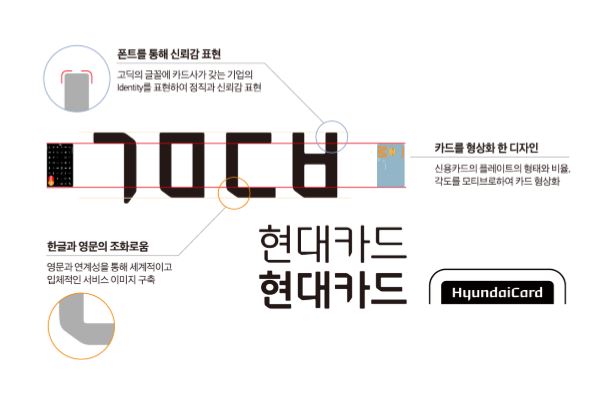
브랜드가 타이포브랜딩을 꼭 해야 하는 이유 5가지
깔끔하면서도 부드러운 느낌의 샌프란시스코(San Francisco)는 애플 폰트로 불릴 만큼 애플의 상징이 되었다. 사용자들은 샌프란시스코체만 보고도 애플을 떠올린다. 이처럼 타이포를 활용한 기업의 브랜딩 활동을 타이포브랜딩이라고 한다. 타이포브랜딩은 어떻게 브랜드의 성공비결이 되었을까? 다섯 가지의 이유를 꼽아봤다.
1. 브랜드의 고유한 목소리가 된다.
기업의 전용서체는 목소리로 비유할 수 있다. 좋은 목소리를 지닌 가수의 음색이 기억에 남듯이, 브랜드의 이미지와 어울리는 서체는 소비자의 기억에 오래 남는다.
카카오는 점점 다양한 형태의 플랫폼으로 사업 영역을 확장하면서 통합적인 디자인을 고민했고, 그 시작으로 ‘카카오체’를 산돌커뮤니케이션과 함께 개발했다.
카카오체는 밝고 재미있고, 친근한 느낌의 감성이 잘 녹아낼 수 있도록 기획되었다. 영문 폰트는 세계적인 디자인 회사인 영국의 달튼막(Daltonmaag)에서 담당하였고, 산돌은 서체를 디자인할 때, 영문과 잘 어울릴 수 있도록 하는 데 공을 들였다고 한다. 귀여운 카카오체는 다양한 플랫폼에 쓰이면서도 카카오의 고유한 색깔을 잘 드러내고 있다.
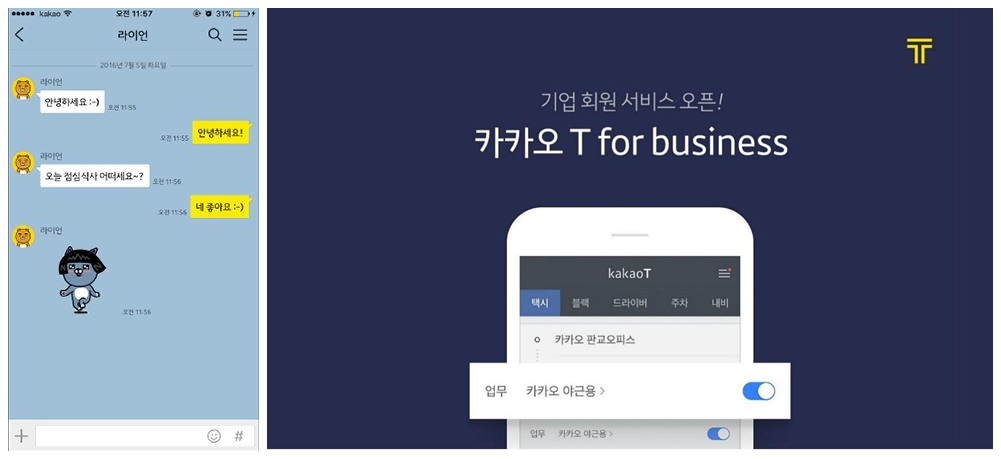
2. 광고비용을 절감할 수 있다.
‘현대카드 유앤아이’ 기업 전용서체는 타이포브랜딩의 대표적인 성공사례로 꼽힌다. 2003년에 제작된 전용서체는 네덜란드 디자인회사 토털 아이덴티티(Total Identity)가 영문 폰트를, 산돌커뮤니케이션이 한글을 개발했다.
카드 모양을 본 따 모서리를 둥글게 디자인함으로써 모던한 느낌을 주며 고딕이 가지는 정직과 신뢰감을 표현했다. 현대카드는 통일된 서체로 브랜딩 활동을 함으로써, 소비자가 서체만 보고도 브랜드를 인식할 수 있게 되었다. 따라서 유명인을 섭외하는데 막대한을 지출을 하지 않고도 타이포만 활용해서 광고제작이 가능했으며, 비용도 절감하는 효과를 가져왔다.
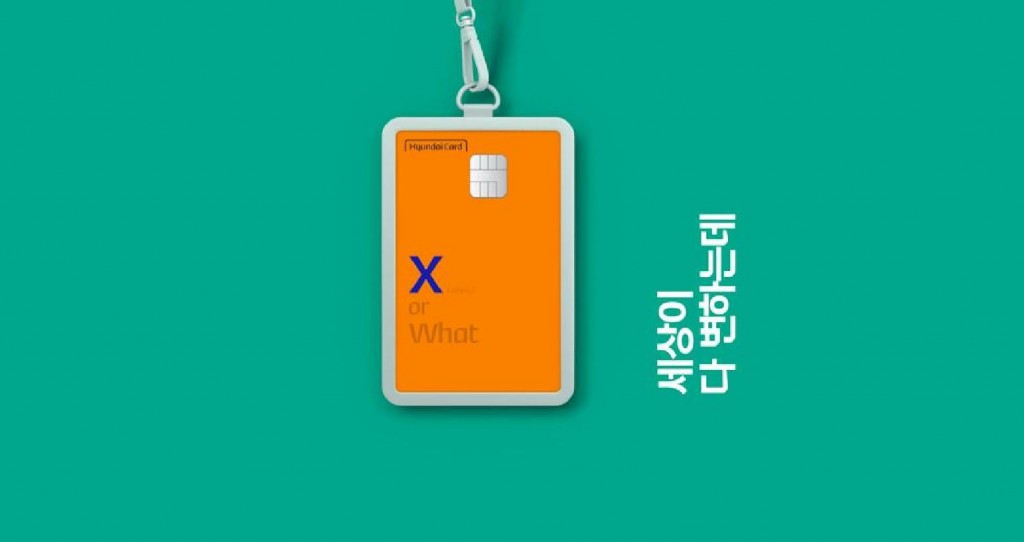
3. 브랜드의 이미지가 된다.
타이포브랜딩은 서체를 통해 상품이나 서비스에 대한 이미지를 형성한다. 산돌커뮤니케이션에서제작한 네이버의 ‘나눔스퀘어체’는 작은 화면에서 봐도 가독성이 높은 서체이다.
네이버는 모바일로 제공되는 수많은 서비스의 톤&매너가 맞지 않아 고민이었고, 통일성을 주기 위해 개발이 시작되었다. 나눔스퀘어는 부가적 요소가 없는 ‘간결함’에 중점을 두고 기획되었다. 이로써 제각각이었던 서비스 톤에 폰트를 활용해서 동일한 브랜드 이미지를 입힐 수 있게 되었다.
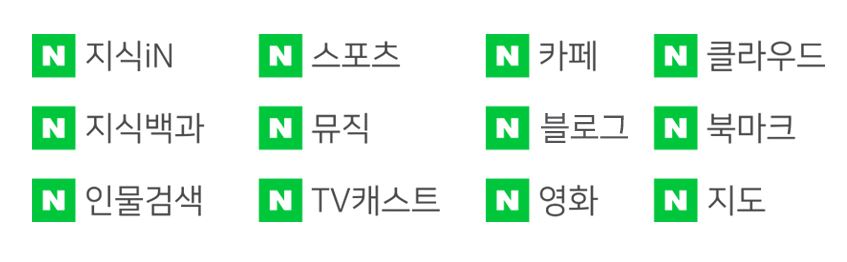
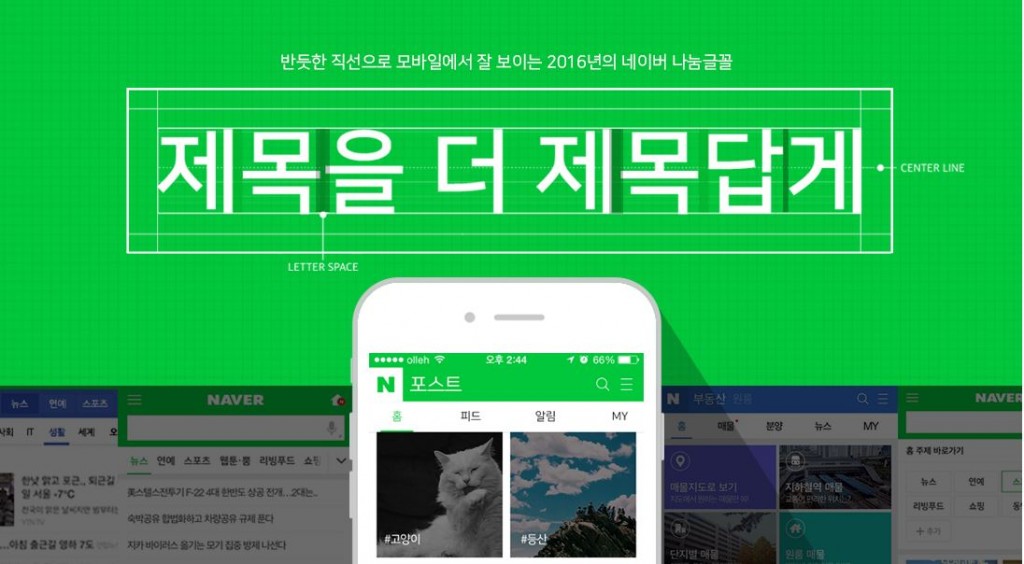
4. 다른 브랜드와의 차별성을 줄 수 있다.
만약 우유를 사러 갔을 때, 모든 상품의 폰트가 똑같다면 어떨까? 특별하게 하나의 제품이 눈에 들어오기는 어려울 것이다. 이때, 개성적인 폰트가 쓰인 상품은 좀 더 쉽게 소비자에게 각인될 수 있다.
윤디자인이 개발한 매일유업의 ‘매일고딕체’는 기업의 반듯한 이미지를 표현하면서도 친근하게 다가가고자 했다. 명확한 직선으로 정직한 기업의 이미지를 보여주고, 맺음 부분을 완만하게 처리하여 친숙하게 표현하고자 했다고 한다.
매일고딕체를 활용한 매일우유는 깔끔한 패키지 디자인과 어우러져, 다른 우유 보다 더욱 돋보이며 맑고 신선한 느낌을 준다.
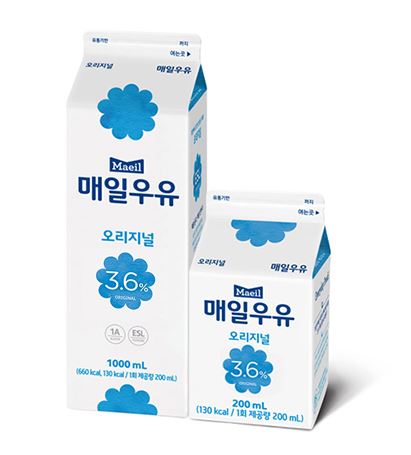
5. 브랜드 아이덴티티를 확고하게 한다.
키치하고 재미있는 마케팅을 펼치는 배달의민족이 광고나 굿즈, 애플리케이션에 명조체를 사용한다면 어떨까? 아무래도 너무 진지해 보여서 어울리지 않을 것이다. 그만큼 브랜딩을 할 때, 기업의 아이덴티티를 고려한 서체는 매우 중요하다.
‘한나는열한살’ 서체는 70~80년대 간판의 키치하고 복고적인 느낌을 현대적으로 재해석한 것이 특징이다. 우아한형제들이 기존에 디자인했던 한나는열한살은 자간이나 글자폭이 맞지 않아 불편함이 있었다. 이를 개선하고자 산돌커뮤니케이션에 리뉴얼 작업을 의뢰하여 프로젝트가 진행되었고, 협업으로 폰트의 완성도를 높일 수 있었다.
배달의민족은 브랜드 색깔과 적합한 폰트를 지속해서 일관되게 사용했기 때문에 브랜드 아이덴티티가 더욱 견고해질 수 있었다.